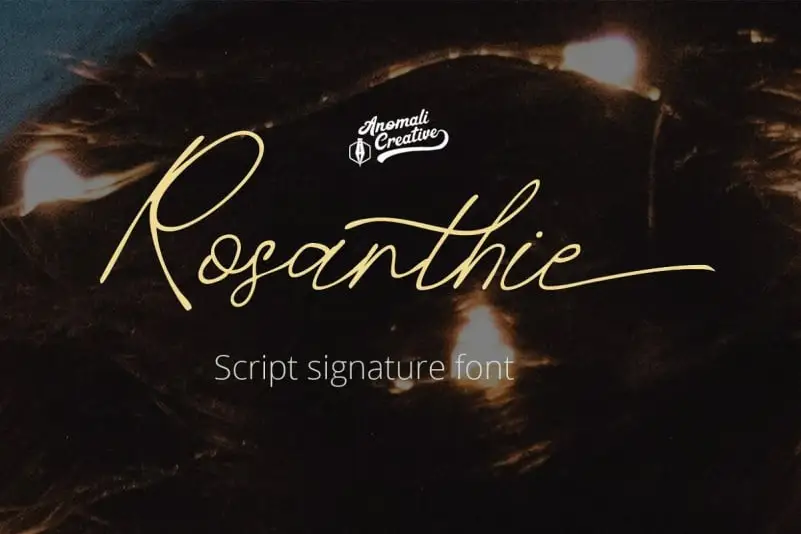
Rosanthie Script Font – Download Grátis
A Rosanthie Script Font é uma nova criação do designer Anomali Creatype. Esta fonte de script é perfeita para estilos de logotipos criativos, citações escritas a mão e embalagens de produtos personalizadas. Seja na web, nas redes sociais, em cartões de aniversário ou mesmo no seu produto, ela oferece um visual elegante e único. A Rosanthie Script Font possui uma ampla gama de letras maiúsculas e minúsculas, alongando-se perfeitamente para textos longos. Também contém um grande conjunto de sinais de pontuação e números, que lhe permitem adicionar riqueza e detalhes a qualquer texto. A fonte também oferece suporte multilíngue, garantindo que ela possa ser usada em diversos contextos culturais e linguísticos. Adotar Rosanthie Script para seus projetos pode transformá-los num elemento diferenciador, criando um design profissional de alto nível. Seja uma marca que deseja transmitir através dos olhos da sua audiência ou um texto personalizado para seu próximo projeto editorial, esta fonte de script será sua melhor escolha.